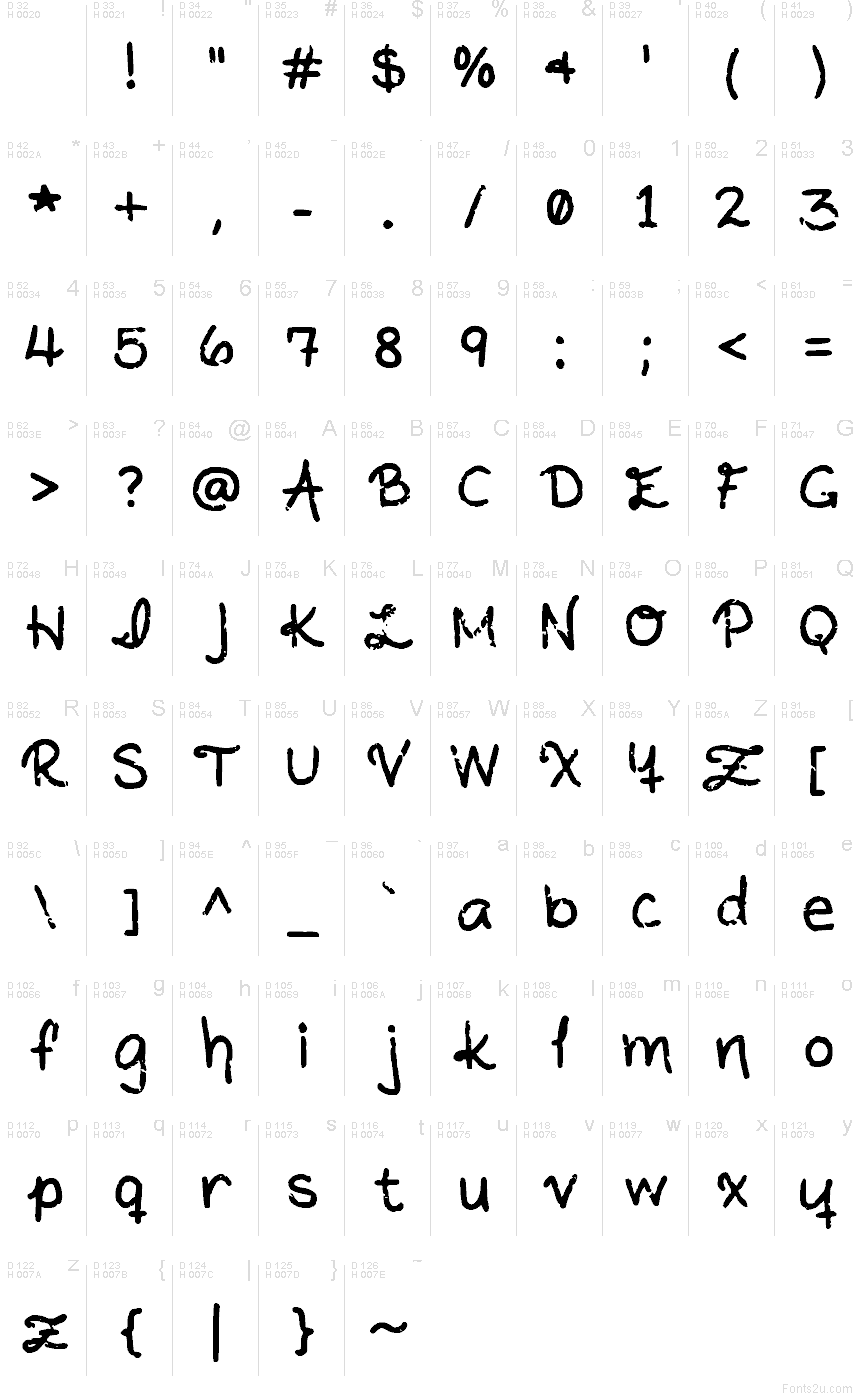
Chalk Regular
Chalkは、黒板に書いたようなチョークスクリプトの無料フォントです。かすれたエッジと、急いで書いた時のような不均一な筆圧が特徴です。丸みを帯びたフォルムと切り詰められたような端、そして手描き特有のリズム感により、親しみやすくも子供っぽすぎない、自然でこなれた雰囲気の文字に仕上がっています。
学校のポスターやカフェのメニューボード、絵本の表紙、ハンドメイドパッケージ、イベントの看板など、手書き感を演出したい場面に最適です。短い見出しやタイトル、ラベルなどに使えば、黒板の粉っぽい質感と、手書き文字ならではの親しみやすさを簡単に追加できます。
Designed to mimic the texture of sidewalk chalk